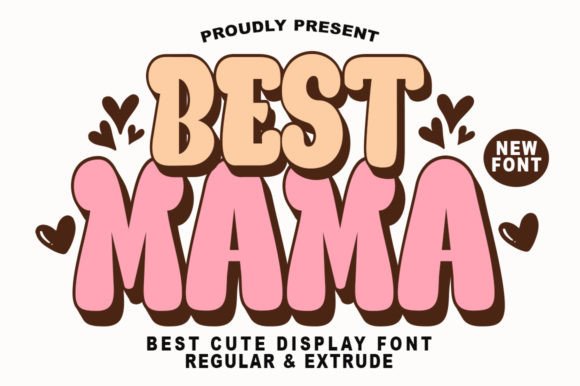
Best Mama Font
Best Mama Font – خط أنيق وعصري يعكس دفء وحنان الأمهات، بتصميم مميز يجمع بين الأناقة والبساطة. مثالي للمشاريع الإبداعية مثل تصميم بطاقات التهنئة، الشعارات، الدفاتر، الديكورات، وغيرها من الاستخدامات التي تحتاج إلى لمسة حميمية وجمالية. احصل على هذا الخط الفريد وأضف لمسات إبداعية إلى تصاميمك!